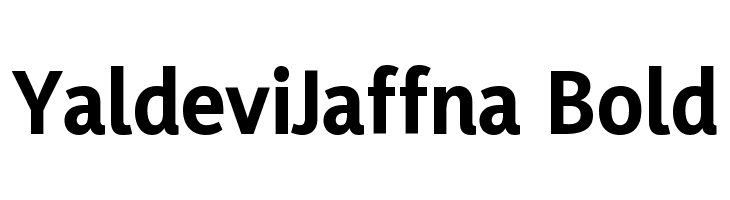
A futuristic, italicized typeface with expanded letterforms and sharp, angular edges.
A high-contrast, decorative font with modern and vintage elements.
A bold, brush-style font with dynamic, textured strokes.
A bold, textured font with characters formed by parallel vertical lines.
A charming handwritten script with smooth, flowing characters.
A bold, textured font with a handcrafted, artistic feel.
A bold, retro-style font with diagonal hatching and a playful, dynamic appearance.
A bold, modern font with high contrast and slightly condensed characters.
A playful, hand-drawn font with tall, narrow letters and a casual style.
A delicate, ultra-lightweight font with thin strokes and minimalistic design.
A whimsical, handwritten font with playful loops and curls.
A bold, stencil-style font with a military-inspired, rugged aesthetic.
A playful, hand-drawn font with a whimsical, ghostly appearance.
A bold, slanted font with a dynamic and energetic style.
A modern, rounded font with consistent stroke width and a playful aesthetic.
A dynamic, brush-style script font with expressive, hand-drawn strokes.
A bold, geometric font with a modern, digital feel.
A bold, geometric font with a strong industrial and futuristic feel.
A playful, handwritten brush-style font with bold, consistent strokes.
A bold, italic serif font with elegant, flowing letterforms and pronounced serifs.
A bold, extruded, and italic font with a modern, dynamic style.
A bold, brush-style font with dynamic, hand-painted strokes.
A bold, geometric font with a three-dimensional, industrial design.
An elegant script font with smooth, flowing strokes and a cohesive cursive style.
A decorative font of masquerade mask illustrations.
A bold, italicized script font with a textured, distressed look.
A bold, geometric font with sharp angles and a futuristic look.
A dynamic, cursive script font with a lively, handwritten style.
A bold, playful outline font with rounded, bubble-like characters.
An elegant monoline italic typeface with a refined and fluid appearance.
An elegant, whimsical script font with flowing, interconnected strokes.